フォントの話をしよう
パイ インターナショナルは2021年8月23日(月)に文字に関わる方必読となる、達人たちの文字&書体の扱い方インタビュー集書籍「フォントの話をしよう」を発売した。
文字のあるところにフォントあり。デザインやことばの印象は、フォントや文字の選び方と組み方で決まる。
エディトリアルや広告などさまざまなフィールドの第一線で活躍されているグラフィックデザイナーに、文字と書体の扱い方をじっくりと取材しました。またフォントメーカー等、フォントや環境を提供する側のお話もあわせて収録しているので、より理解を深めることができる。
書体選びのコツからオリジナル文字のデザインまで、実例作品を通じ、タイポグラフィがすーっと理解できる1冊となる。
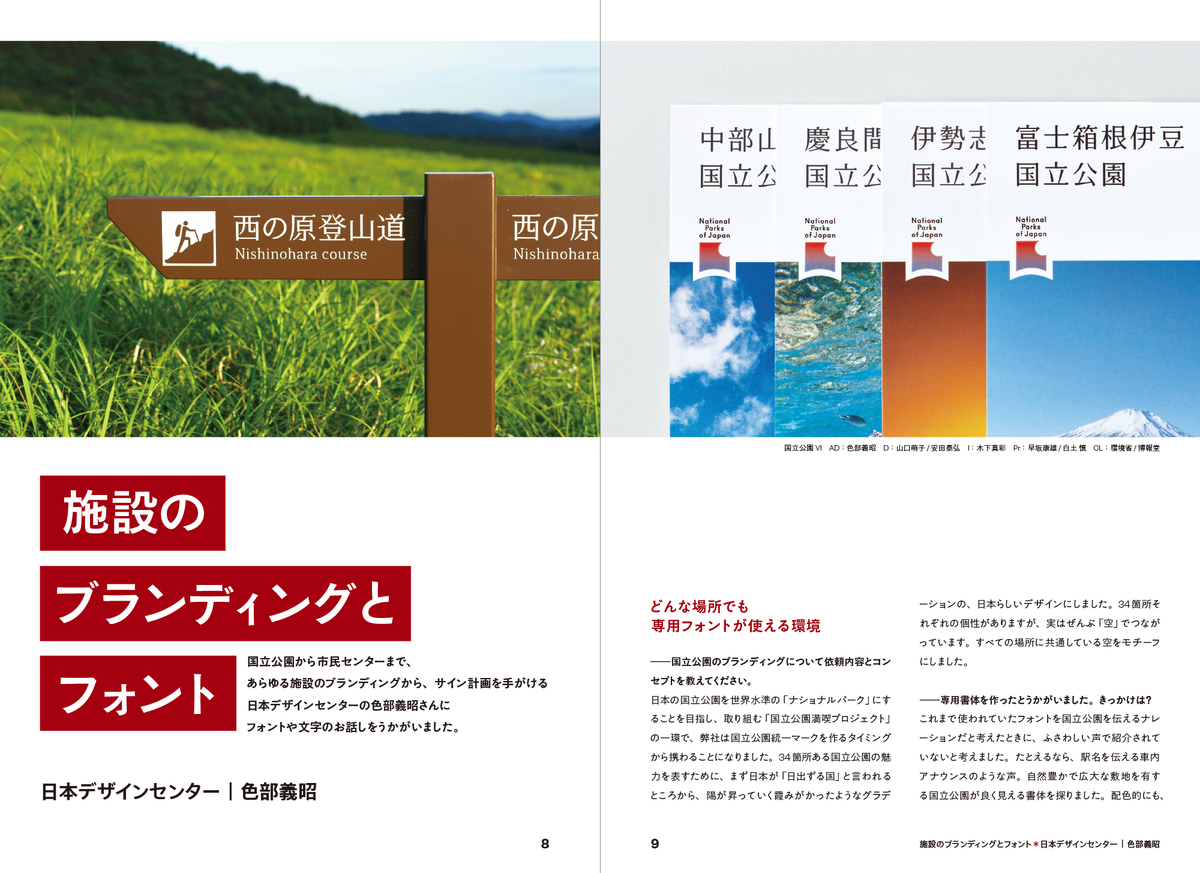
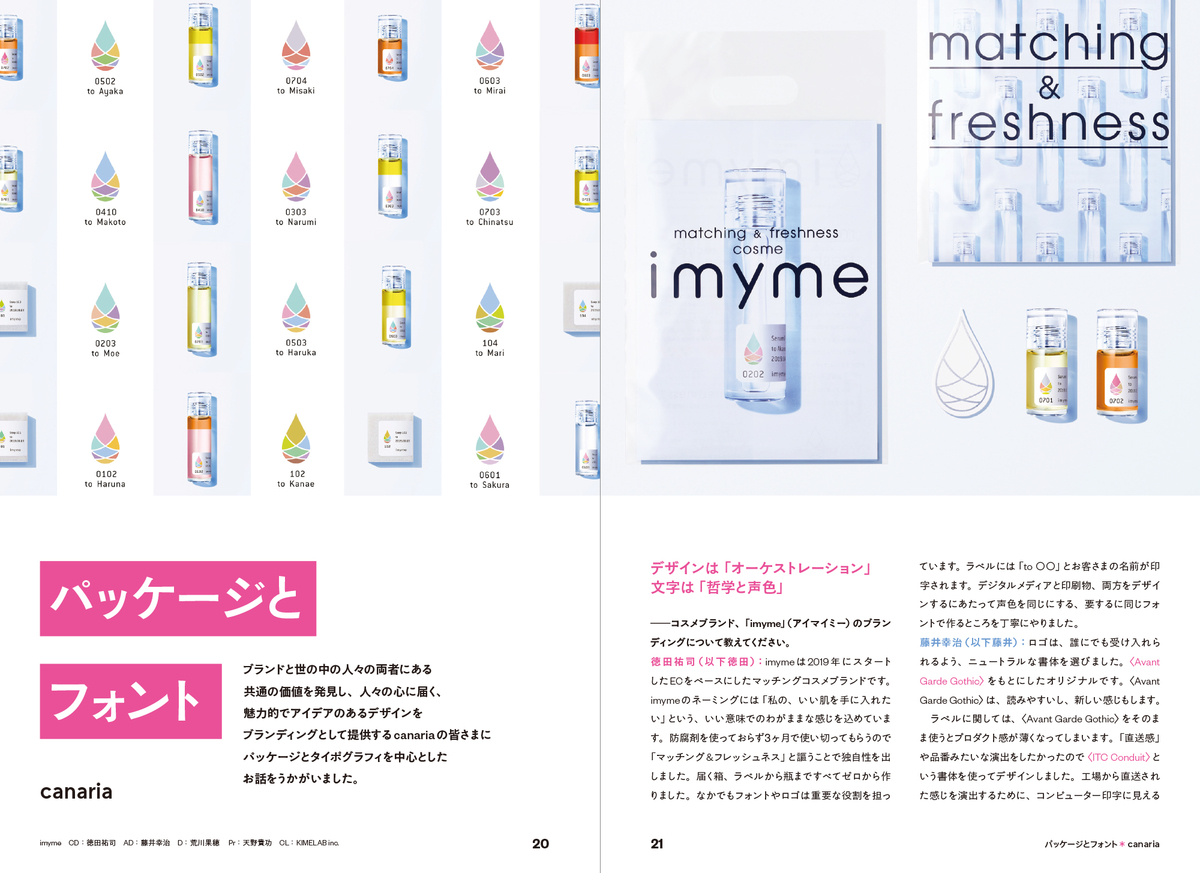
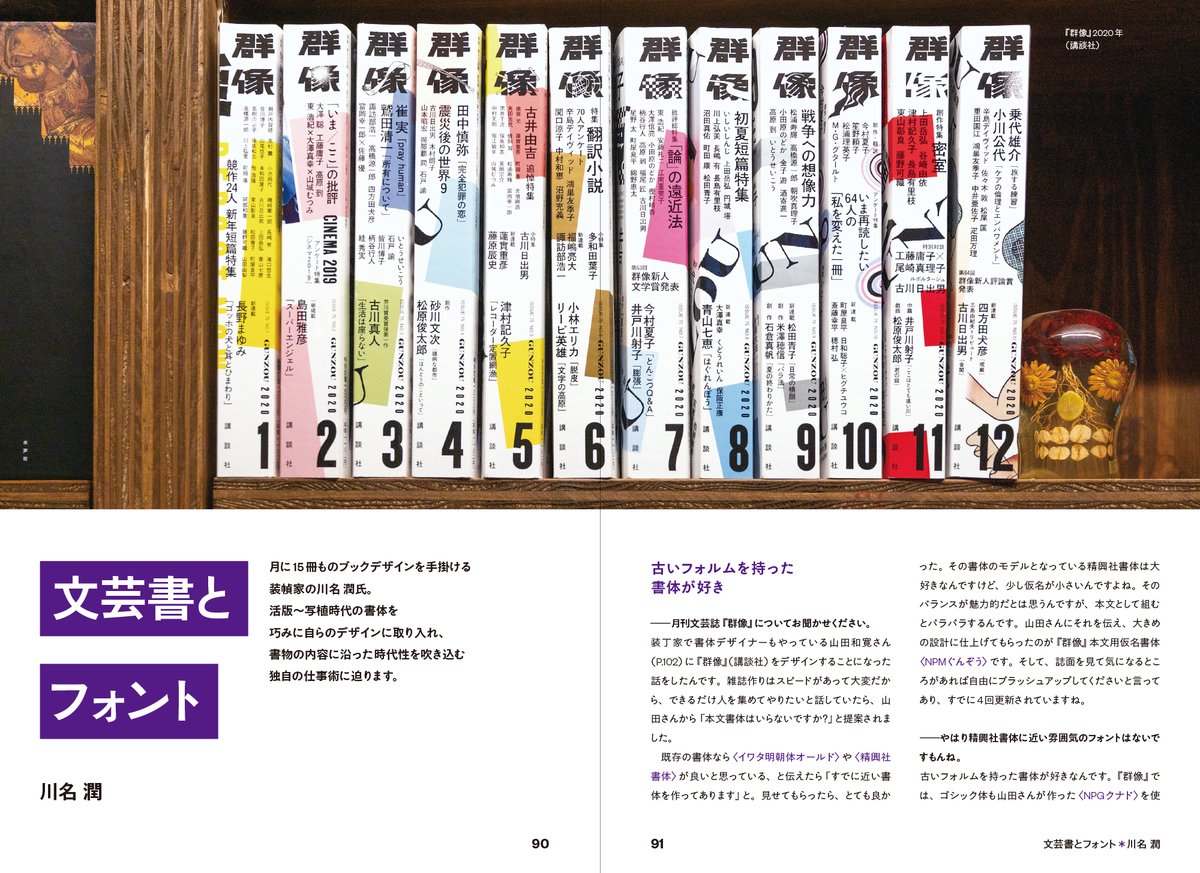
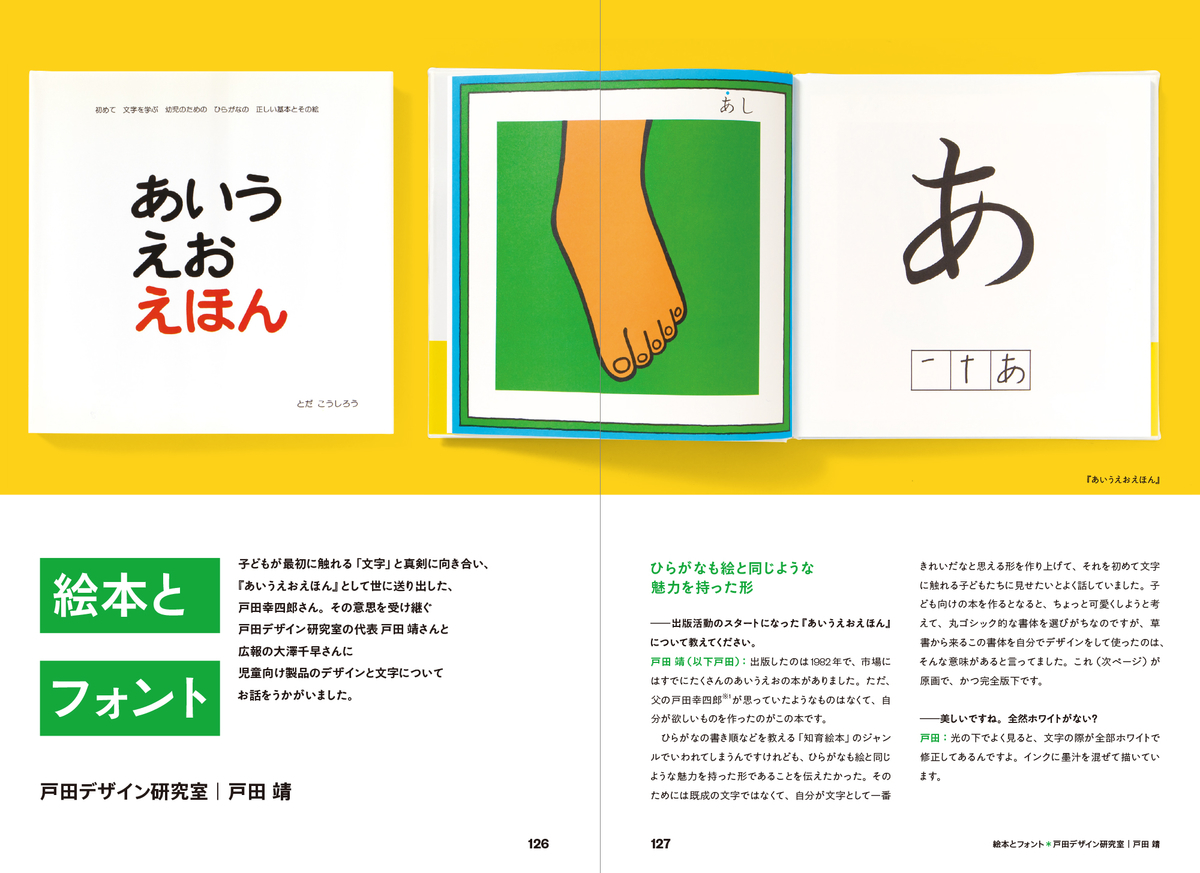
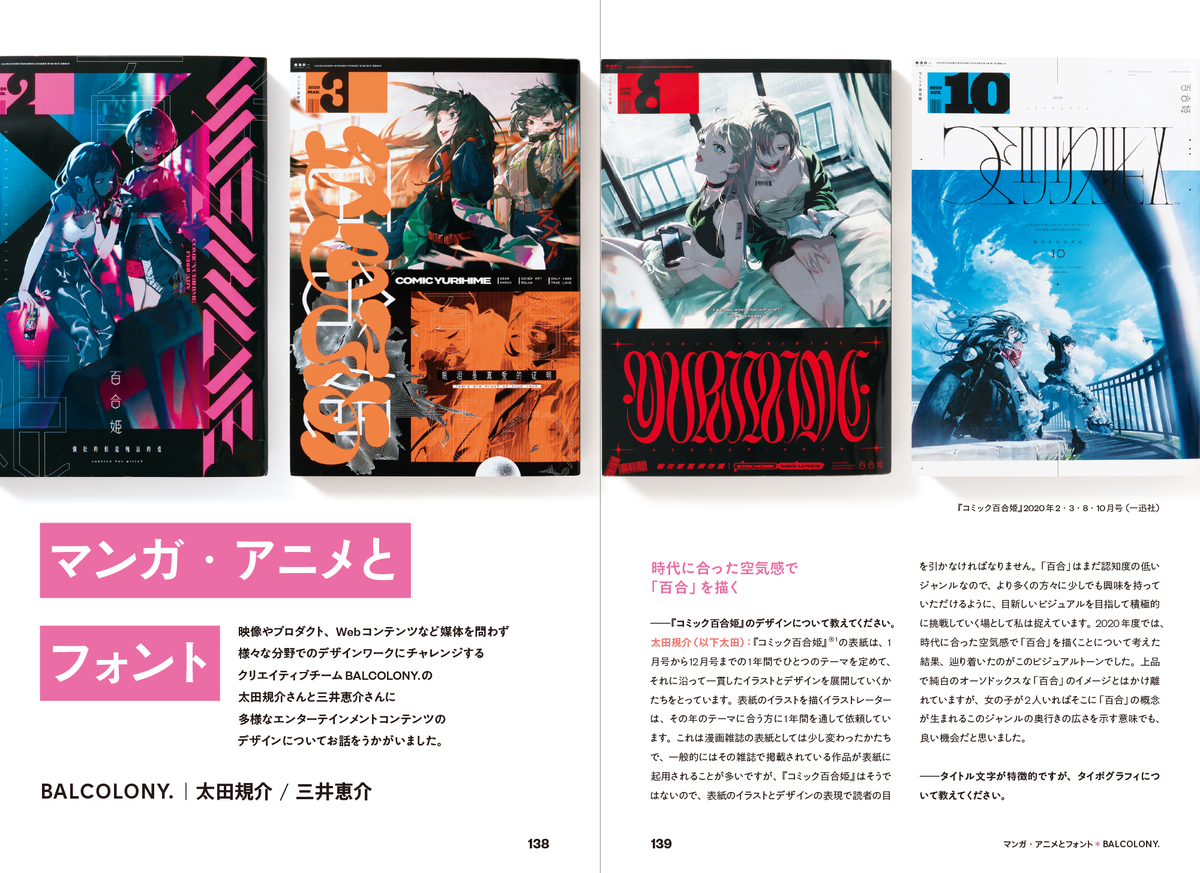
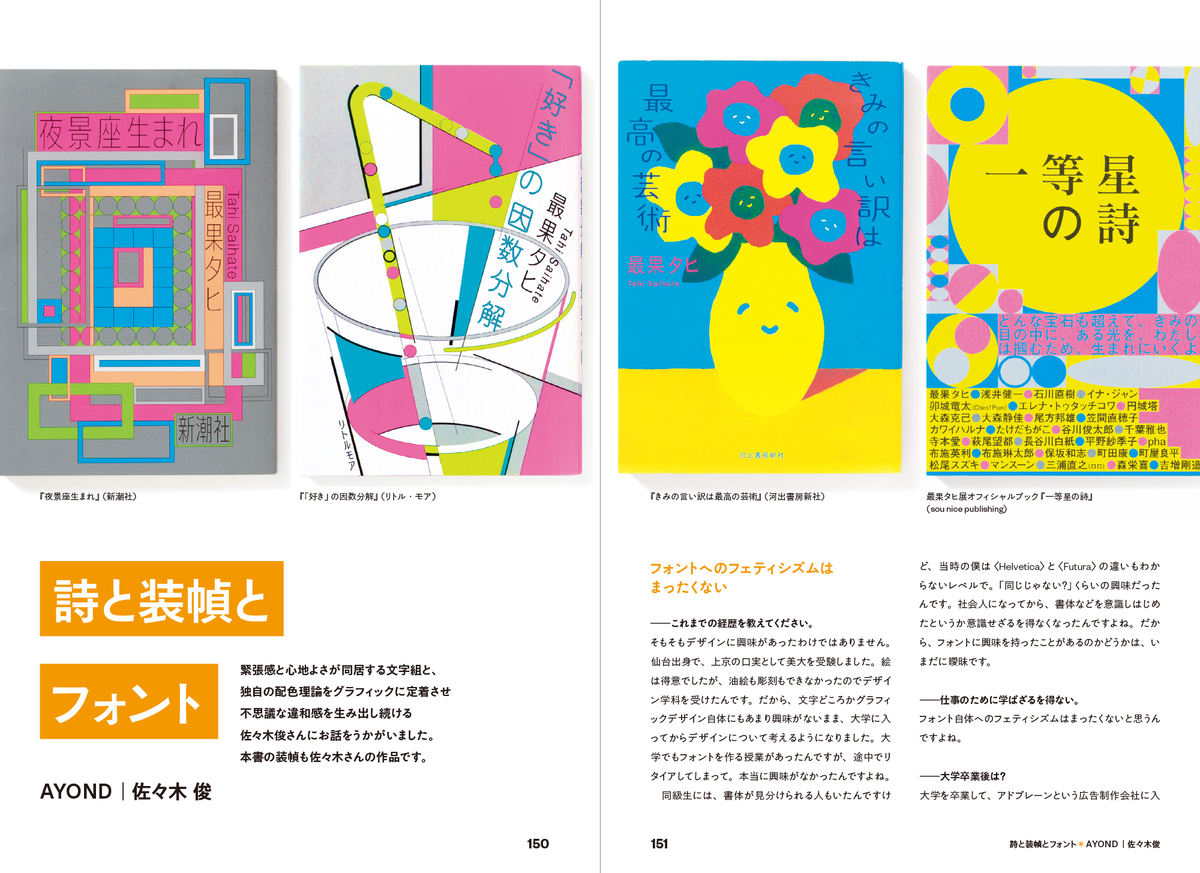
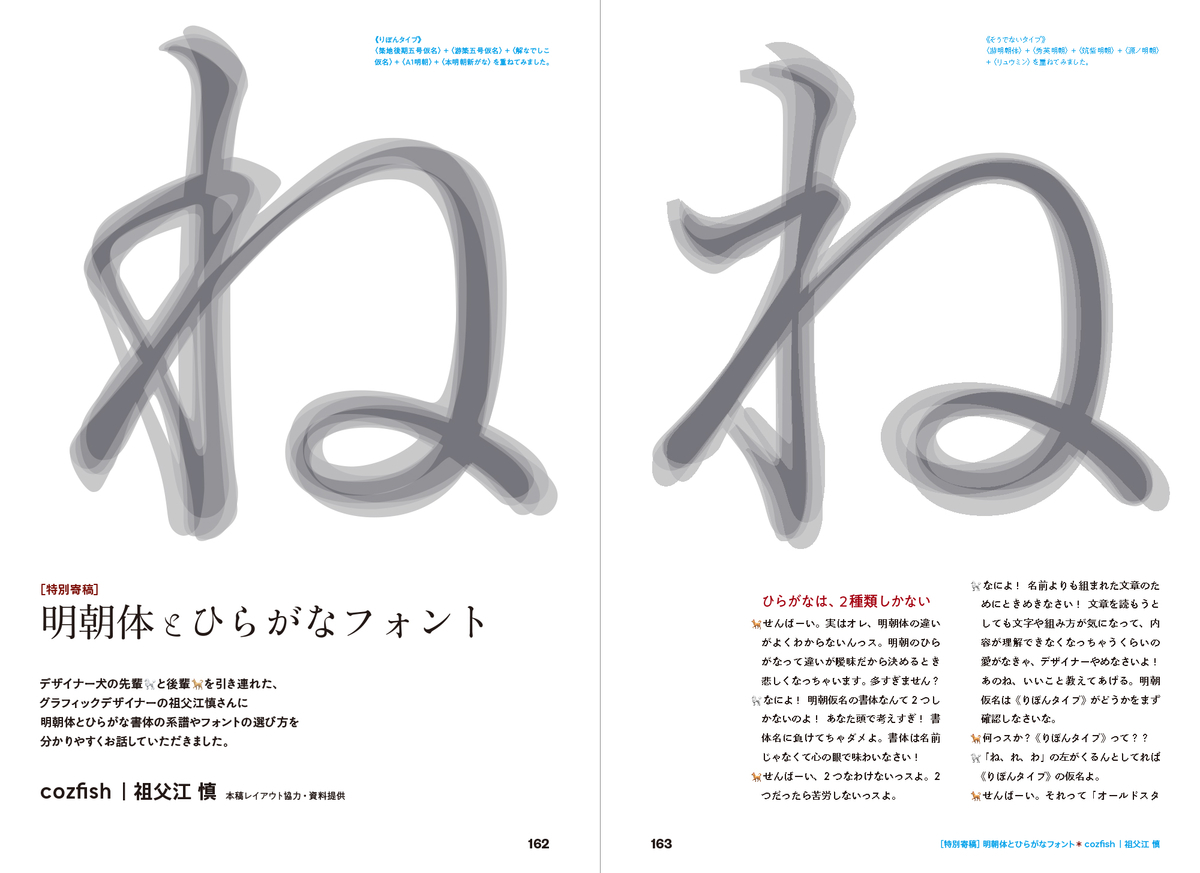
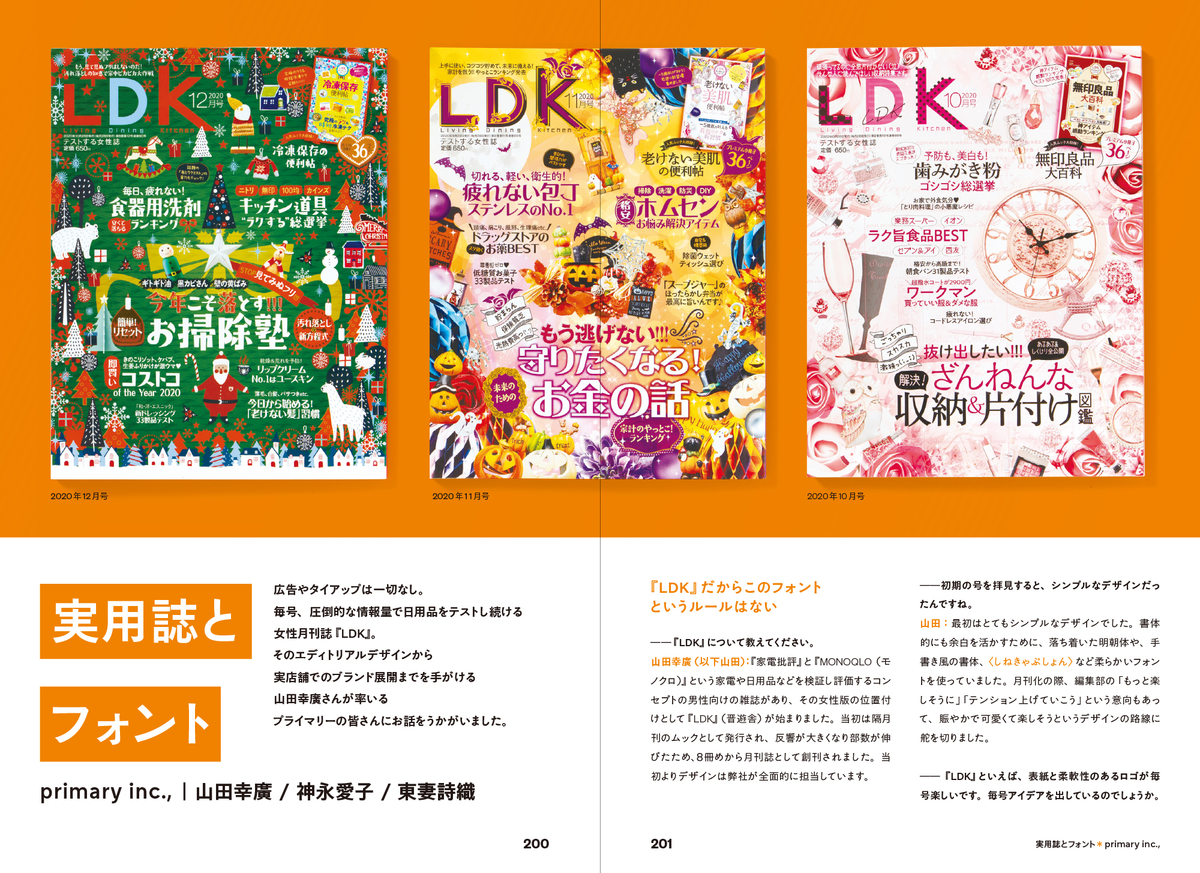
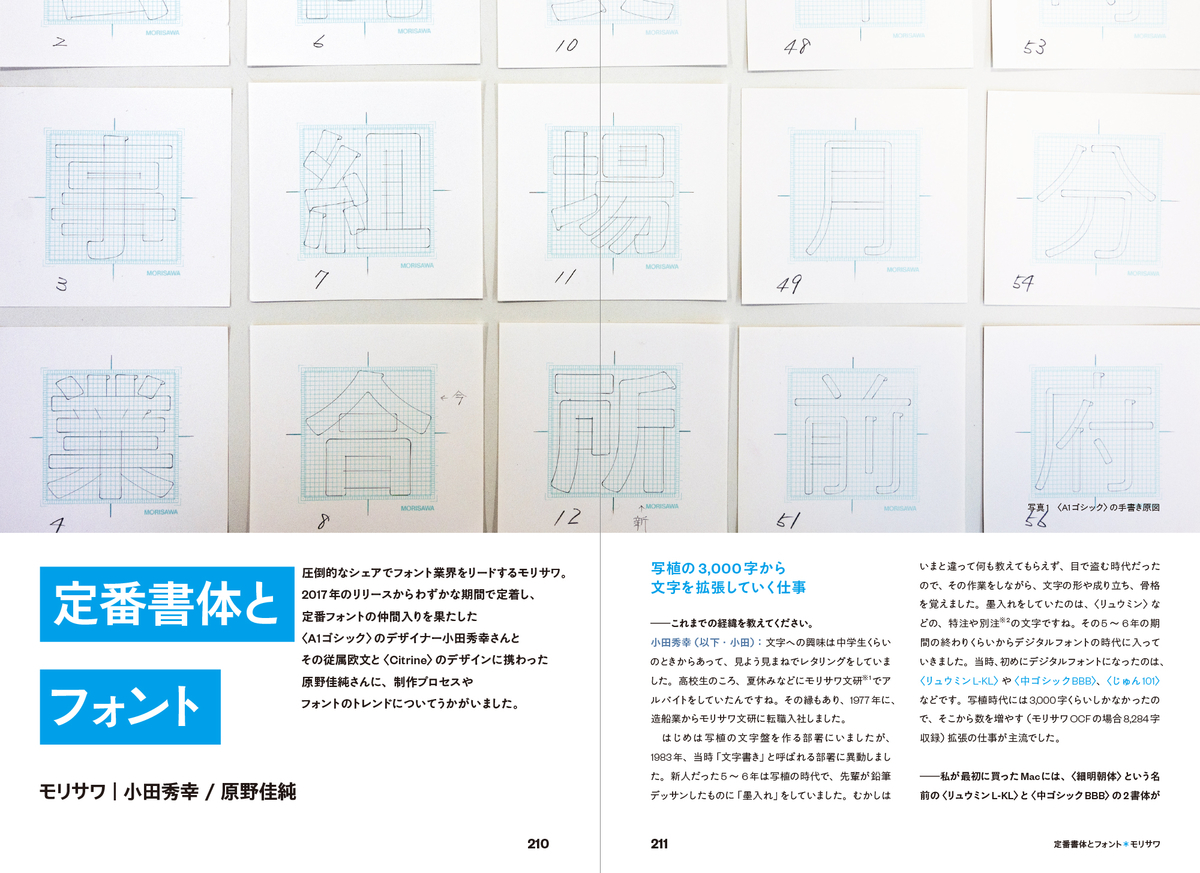
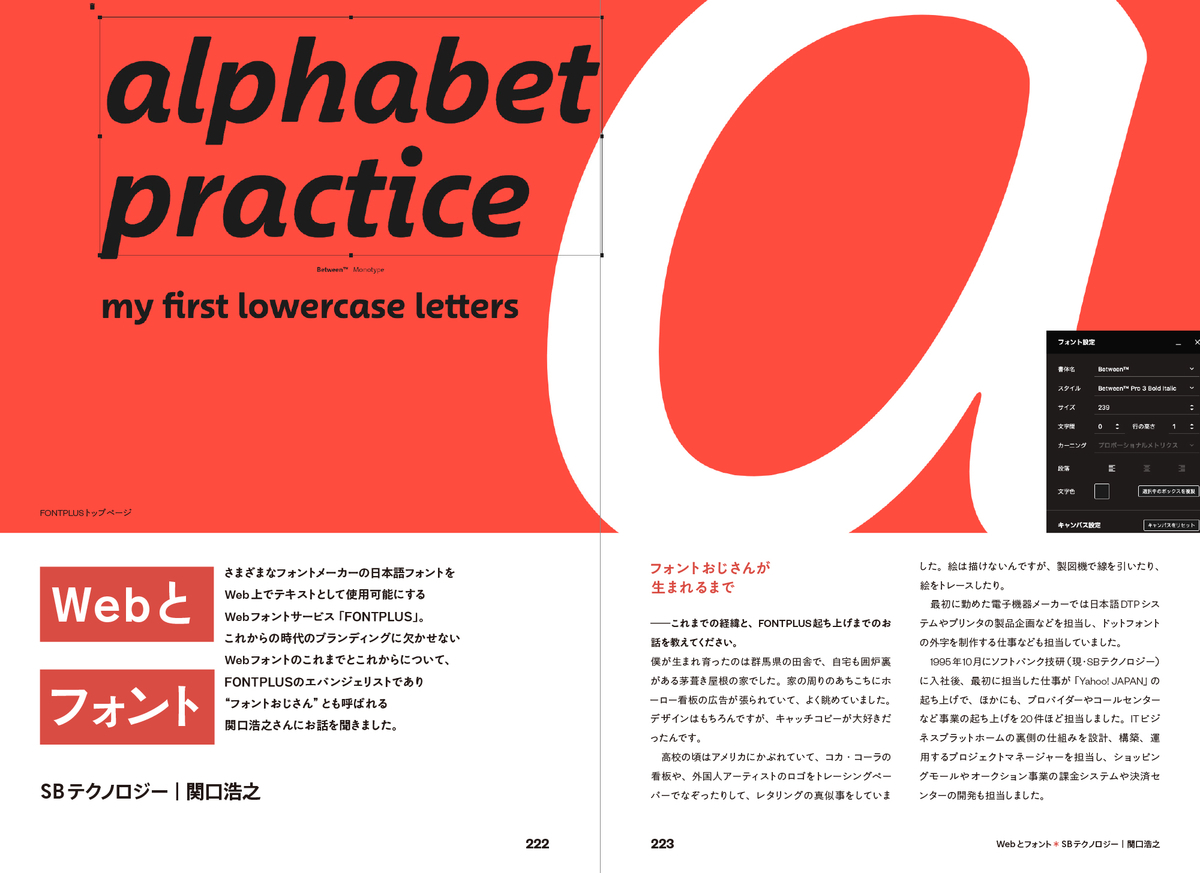
「フォントの話をしよう」インタビュー者一覧(掲載順)
◎ブランディングとフォント
日本デザインセンター|色部義昭、canaria、ライツデザイン|中市 哲、DODO DESIGN|堂々 穣、MIMIGURI|今市達也、TBSテレビ デザインセンター|團野慎太郎、タイププロジェクト|鈴木 功
◎ブックデザインとフォント
川名 潤、nipponia|山田和寛、tento|漆原悠一、戸田デザイン研究室|戸田 靖、BALCOLONY.|太田規介 / 三井恵介、AYOND|佐々木 俊、cozfish|祖父江 慎
◎雑誌、Webデザインとフォント
ビーワークス|佐伯麻衣 / 嶽野甲子郎、ma-hgra|田中清賀、primary inc.,|山田幸廣 / 神永愛子 / 東妻詩織、モリサワ|小田秀幸 / 原野佳純、SBテクノロジー|関口浩之